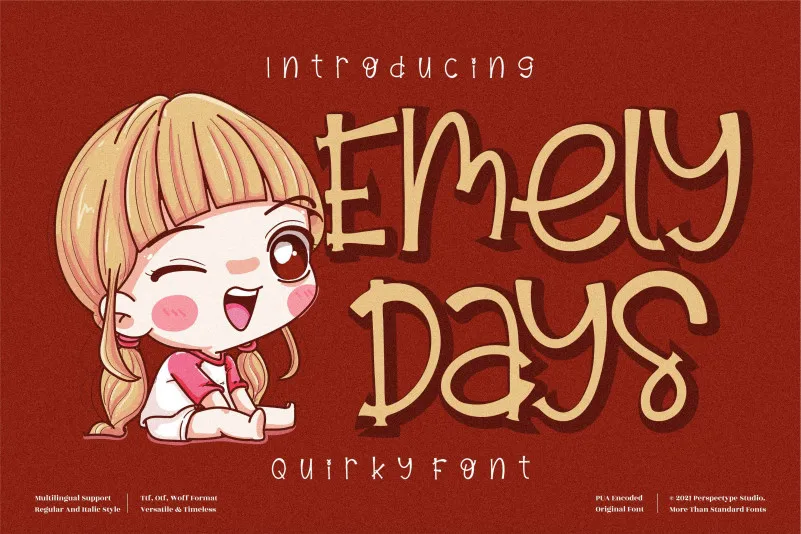
Emely Days Font – Download Grátis
A fonte ‘Emely Days’ é uma seleção divertida e única para designers casuais ou pro que buscam dar um toque criativo a suas criações. Desenvolvida pela perspectype, ela se destaca como uma escolha ideal para trabalhos relacionados à arte desenhada, jogos infantis ou qualquer projeto que necessite de uma aparência agradável e descontraída. Suas formas manuscritas, com seus traços fluidos e desenhos levemente caricatos, garantem um toque colorido e animado para seus designs. Seja você criando um game infantil ou artificando um layout de blog infanto-juvenil, a ‘Emely Days’ irá certamente trazer uma pitada divertida e pessoal ao seu trabalho. Para designers que procuram um elemento único e divertido na sua biblioteca de fontes, esta é uma escolha perfeita.